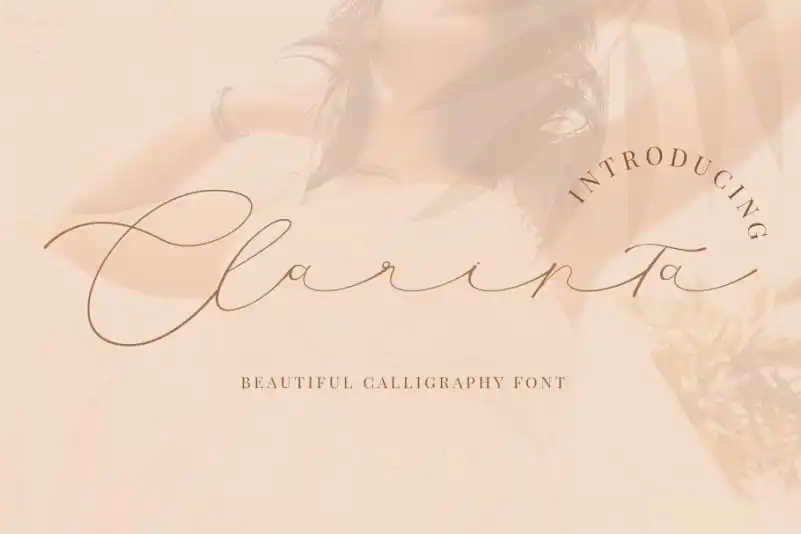
Clarinta Calligraphy Font – Download Grátis
A fonte ‘Clarinta Calligraphy’ foi criada para se parecer ao máximo com uma escrita a mão natural, incluindo mais de 134 ligaturas e alternativas minúsculas personalizadas. Desenvolvida pelo designer PutraCetol Studio, essa font tem um charme delicado e elegante, com traços fluidos que se movem harmoniosamente entre as letras. O resultado é uma fonte perfeita para estilos de logos, cartões de papelaria, eventos casais, convites, frases inspiradoras, redes sociais e websites, sendo uma opção versátil e elegante para diversos projetos. Com suas combinações perfeitamente equilibradas, a font ‘Clarinta Calligraphy’ complementa facilmente um amplo leque de designs.